21 melhores fontes punk de 2023 (grátis e premium)
Publicados: 2023-10-02Você é um designer gráfico que deseja adicionar um pouco de ousadia aos seus projetos?
Você está cansado de usar as mesmas fontes antigas que todo mundo usa? Bem, não procure mais porque temos a solução para você – Punk Fonts! Nesta postagem do blog, exploraremos o mundo das fontes punk e como elas podem levar seus designs para o próximo nível.
Agora, eu sei o que você pode estar pensando – “Fontes Punk? O punk não é tudo sobre rebelião e anarquia? Como isso pode ser traduzido em uma fonte?” Bem, meu amigo, é exatamente nisso que vamos nos aprofundar.
Punk Fonts são um estilo único de tipografia que incorpora a essência da cultura punk – crua, corajosa e rebelde. Essas fontes podem adicionar um toque de atitude e energia aos seus designs, fazendo com que se destaquem da multidão.
Mas não acredite apenas na minha palavra. Você sabia que usar fontes punk pode realmente melhorar o design geral dos seus projetos?
De acordo com um estudo da DesignContest, incorporar tipografia não convencional pode levar a um aumento de 40% no envolvimento do usuário. É isso mesmo – simplesmente trocando as fontes, você pode capturar a atenção do seu público e mantê-lo preso.
Portanto, neste artigo exploraremos os diferentes tipos de fontes punk disponíveis e como você pode usá-las de forma criativa em seus designs.
Esteja você trabalhando em um site, um pôster ou um logotipo, nós ajudamos você. Prepare-se para libertar seu rebelde interior e revolucionar seus projetos de design com o poder das fontes punk. Vamos mergulhar!
Melhores fontes punk premium
Procurando adicionar um toque rebelde aos seus projetos de design? Não procure mais, nossa seleção das melhores fontes punk premium.
Prepare-se para infundir em seus designs uma vibração ousada e energética que deixará uma impressão duradoura em seu público. Confira abaixo essas fontes obrigatórias e solte sua criatividade!
Steampunk
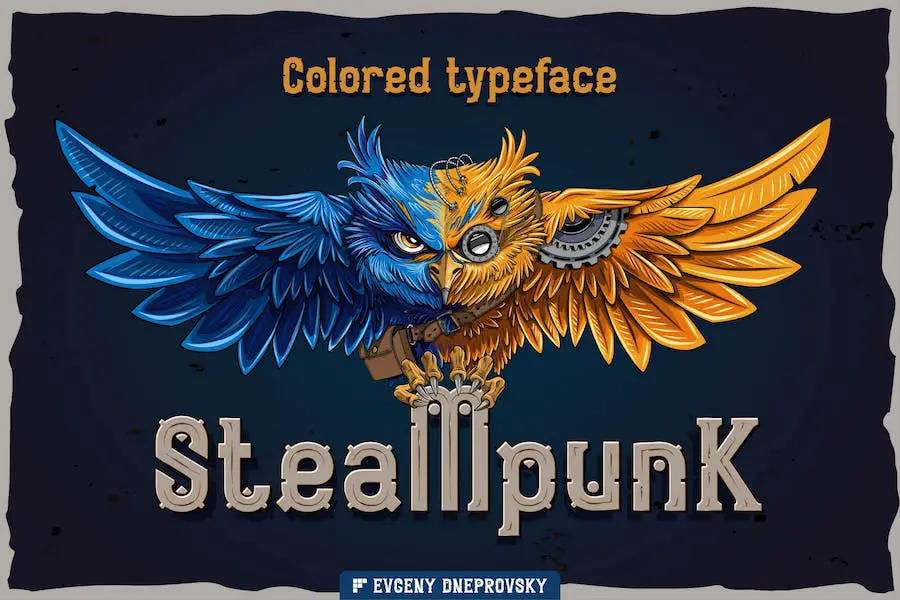
Steampunk é uma fonte vetorial bônus que apresenta um design único e cativante, perfeita para designers gráficos que buscam aprimorar seus projetos com um toque de estética punk. Esta fonte vem em cinco estilos diferentes, incluindo três fontes pretas e duas fontes coloridas.
Com seu tema coruja steampunk, esta fonte adiciona uma vibração rebelde e ousada a qualquer design. Os detalhes intrincados e os traços ousados das letras criam um efeito visualmente marcante.
Esteja você trabalhando em um pôster, logotipo ou site, Steampunk certamente chamará a atenção do seu público.
Com sua coruja vetorial bônus, esta fonte Google Punk fornece um elemento extra que pode ser usado para aprimorar ainda mais seus designs. A coruja simboliza sabedoria e conhecimento, acrescentando um toque de sofisticação e intriga às suas criações.
Punk enferrujado
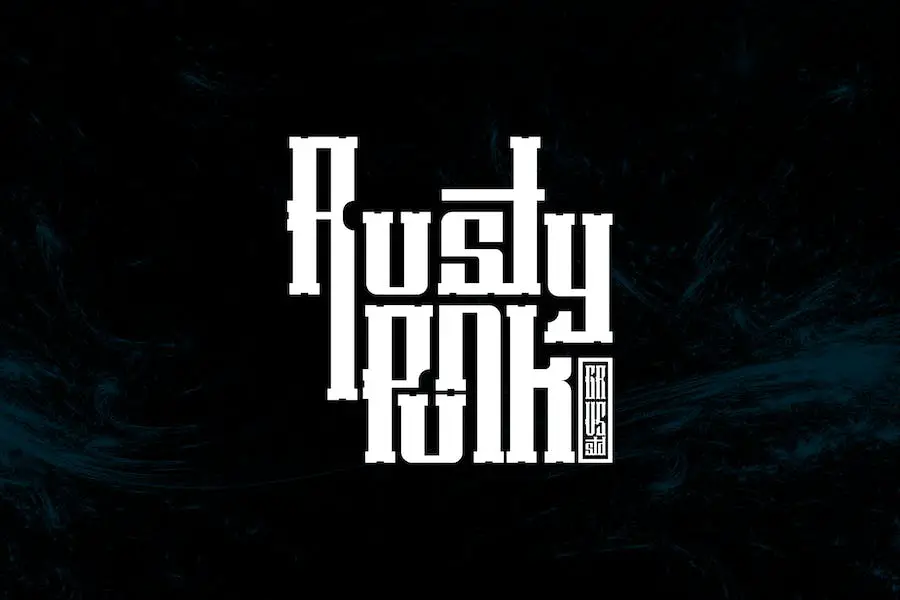
Rusty Punk é uma fonte chamada 'GRVS It Font' que é perfeita para criar um logotipo de equipe ou comunidade com tema steampunk.
Com esta fonte Adobe Punk, você pode adicionar um toque único e ousado aos seus projetos de design gráfico. Esteja você trabalhando em um logotipo para uma equipe ou em um adesivo legal, essa fonte ajudará a dar vida à sua visão.
Então, por que esperar? Dê aos seus projetos uma vibe punk com Rusty Punk!
Punk Gibson
Punk Gibson é uma fonte única e ousada, perfeita para designers gráficos que buscam adicionar um toque de inspiração punk aos seus projetos. Com suas pinceladas legais e ousadas, essa fonte adiciona um nível de detalhe que dá a aparência de tinta seca.
Essas fontes Punk para Word são especialmente ótimas para aplicações esportivas e de design urbano, como pôsteres, embalagens, publicidade, manchetes, marcas e sinalização. É versátil e pode ser usado para o que vier à mente.
A fonte está disponível em três larguras diferentes: estreita, regular e larga, permitindo que você escolha o ajuste perfeito para o seu projeto. Ele suporta caracteres latinos básicos, numerais e pontuação, e ainda oferece suporte multilíngue para a, o, u, Ä, O e U.
Punk Havaiano
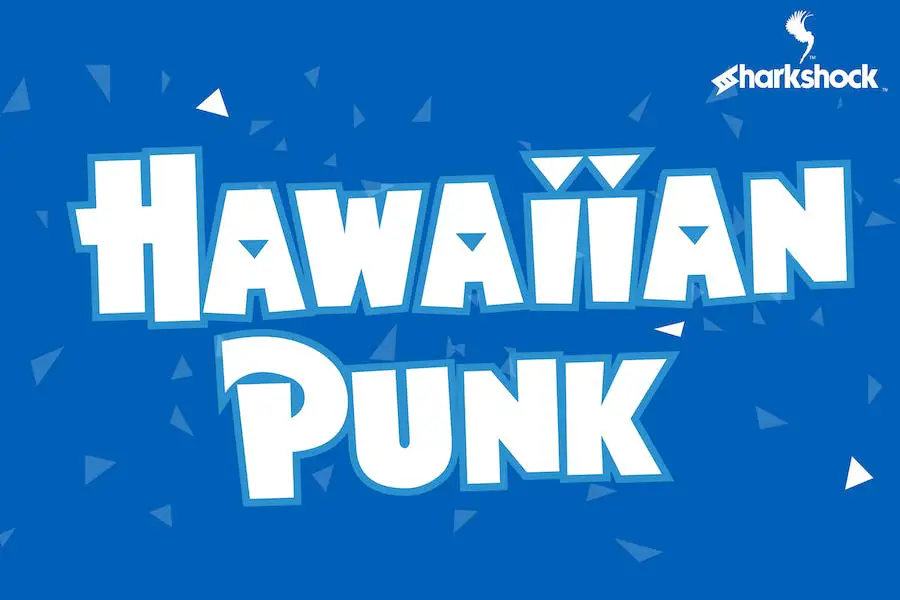
Hawaiian Punk é uma fonte divertida que traz uma vibração tropical aos seus designs. Esta fonte display sans serif tem tudo a ver com diversão e emoção, e não se leva muito a sério. Seu design é tropical e vibrante, mas mantém uma execução simples e direta.